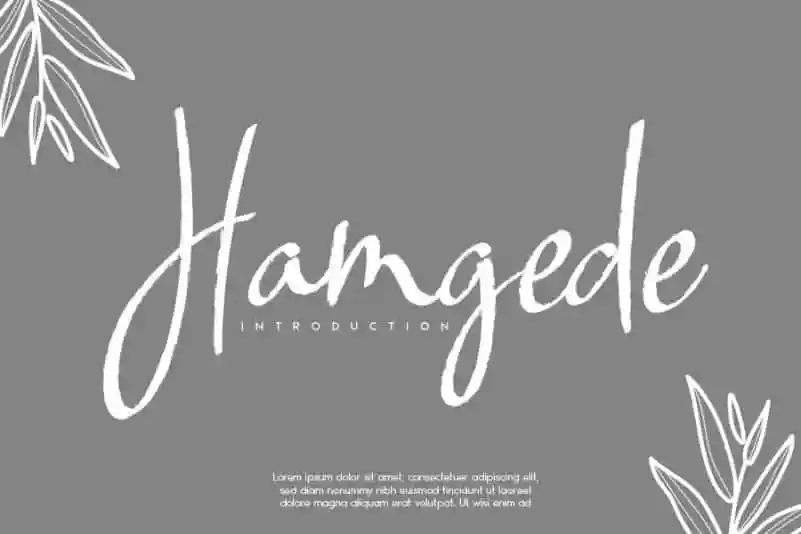
Hamgede Handwritten Font – Download Grátis
Hamgede Handwritten Font é uma elegante e única fonte escrita a mão que traz consigo um estilo único. Suas linhas delicadas se destacam como um recurso perfeito para vários contextos, desde design de logotipos até criação de websites pessoais. Sua personalidade distintiva permite incorporá-la em qualquer projeto favorito e apreciar a transformação que ela causa. Hamgede Handwritten Font é uma fonte de brush ideal, oferecendo aos designers um recurso visual poderoso para destacar seus trabalhos. Seja você criando um site minimalista ou montando seu próprio livro de recados, Hamgede garantirá que sua mensagem seja ainda mais emocional e atraente. Nesse sentido, não há dúvida de que este é um recurso fundamental no arsenal de qualquer designer gráfico.